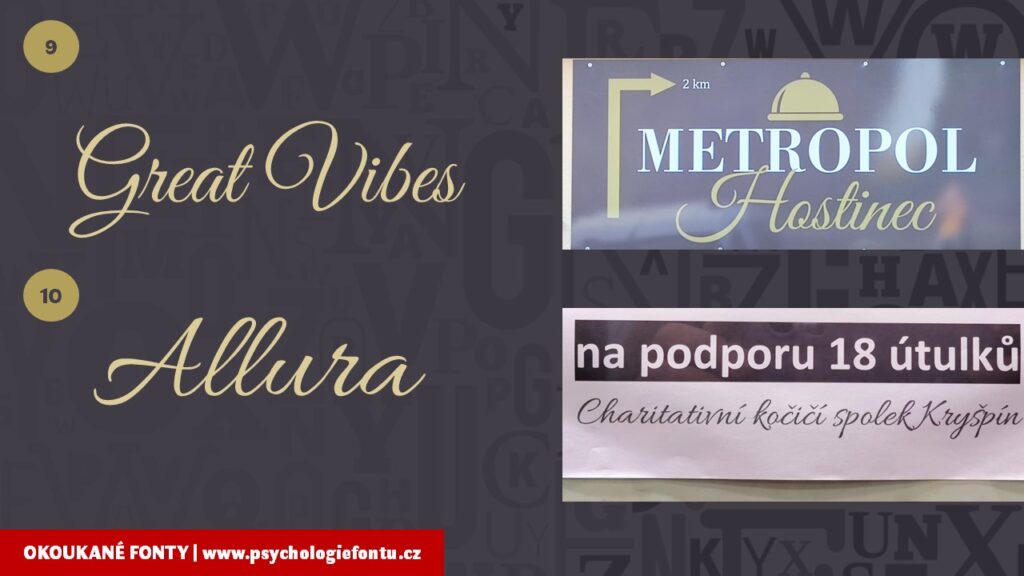
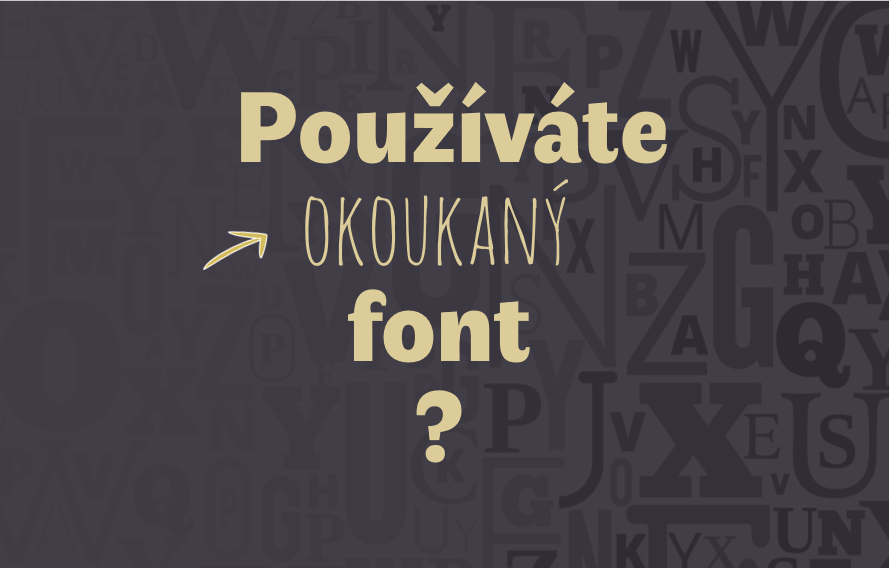
Jsou jako trpaslíci. Skáčou na vás i z ledničky, a to doslova. Fonty, které můžete potkat na ceduli „párek v rohlíku“, na oznámení Českých drah i na vývěsním štítu Beauty salonu. Mluvíme o fontech, které používají miliony lidí na celém světě bezmyšlenkovitě a bez záměru.
Fontech okoukaných.
A takové nechcete. Pokud nemáte rádi trpaslíky.
Pozor, ve většině případů to nejsou fonty špatné, naopak. Až na skupinu fontů amatérských, které náhodou spadnou do aktuálního trendu a stanou se na pár týdnů slavnými. Okoukané fonty mají tu smůlu, že byly zajímavé, originální a snadno dostupné. A v té kombinaci je zakopaný pes.
Sáhnete po nich bezmyšlenkovitě, často jako první volbu, a vůbec netušíte, že se jejich použitím stáváte jedním z mnoha identických trpaslíků. V lepším případě. Protože v horším případě potkáte spoustu lidí, kteří jsou na trpaslíky alergičtí. A na okoukané fonty také.
To, že je font okoukaný, může mít různé důvody. Pojďme si je prozkoumat. A hlavně, pojďme se podívat na to, které fonty to jsou, ať se jim můžete vyhnout.
Ano, okoukaných fontů je mnohem více, toto je výběr. Ano, je to výběr subjektivní, založený na 10leté praxi člověka, který denně analyzuje úplně každý font, který potká, ať online nebo offline.
Neberte si osobně, pokud v ukázkách najdete i váš font, ale vezměte to jako příležitost zase se o kousek posunout dál a vyměnit ho.
Jsou jako Mončičáci (pro pamětníky) nebo Labubu.
Každá doba má své fonty, které frčí. Možná prezentují energii doby, možná potřeby lidí a možná je to náhoda. Možná font použila nějaká celebrita, kterou kopírují tisíce obdivovatelů.
Průkopníkem tohoto trendu byl nešťastný Comic Sans, který doplatil na svou originalitu (ano, Comic Sans BYL ve své době originální!). První font z kategorie handwriting mezi patkovými a bezpatkovými fonty. Navržený Vincentem Connarem r. 1994, speciálně pro komiks o pejskovi Roverovi.
A jak dopadl. Dopracoval to až ke vzniku celosvětového hnutí Ban Comic Sans, strhávání všech tiskovin, na kterých byl použitý z výloh a jejich ostentativní ničení. Stojí za nejedním nervovým tikem grafických designérů, kteří se snaží diplomaticky odmítnout nejoblíbenější font klienta.
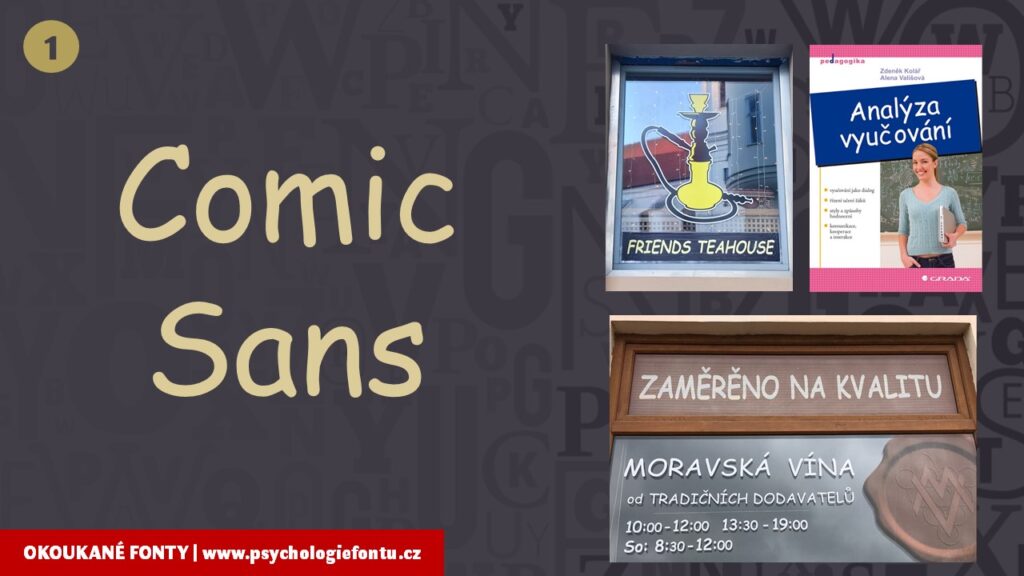
A je mu nahouby, že je neformální, přátelský a velmi dobře čitelný. Že ho milují lidé s dyslexií, děti a lidé slabozrací, protože se jim opravdu dobře čte.
Ale pověst je pověst, abyste si nezadali a nespustili se s „persona ingrata“, nezbývá, než okoukané fonty nahradit jinými, které v sobě nemají negativní podtext „šmarjá už zase!“.
Třeba u hollywoodského trháku, který má rozpočet v miliardách, vám použití druhého nejvíce okoukaného fontu, který je pro grafiky noční můrou, hlava nebere…
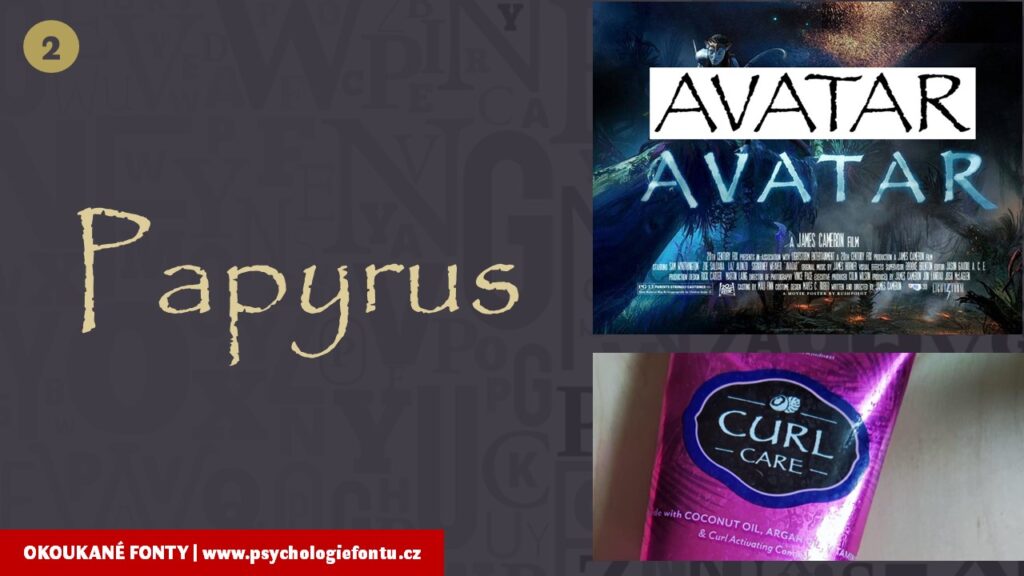
Příklady některých z „populárních“ fontů, které vévodily v popularitě v posledních 10 letech:
Comic Sans, Papyrus, Segoe Script, Amatic SC, Algerian, Scriptina (Ze stejné škatulky jako Scriptina je okoukané Zapfino).
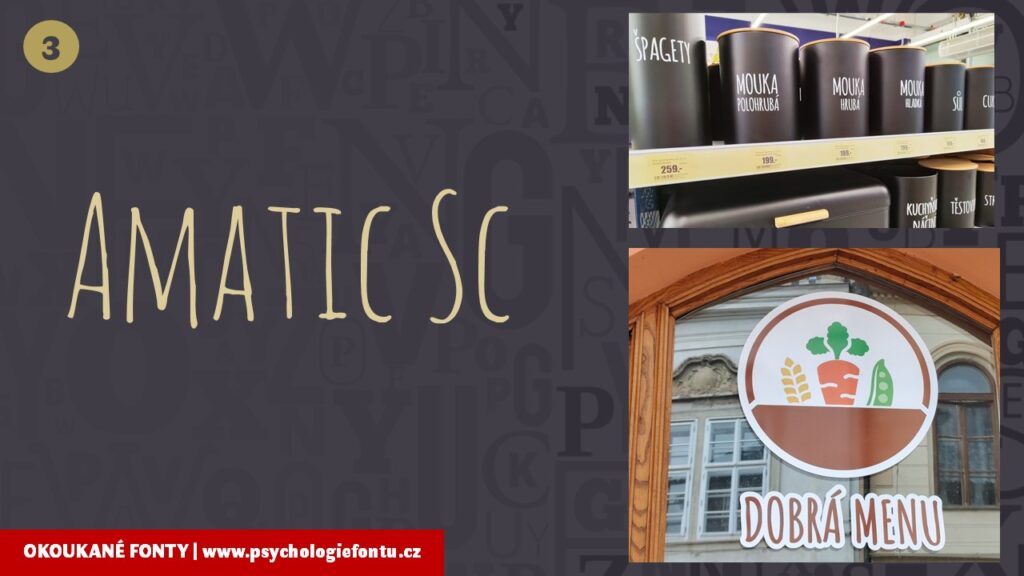
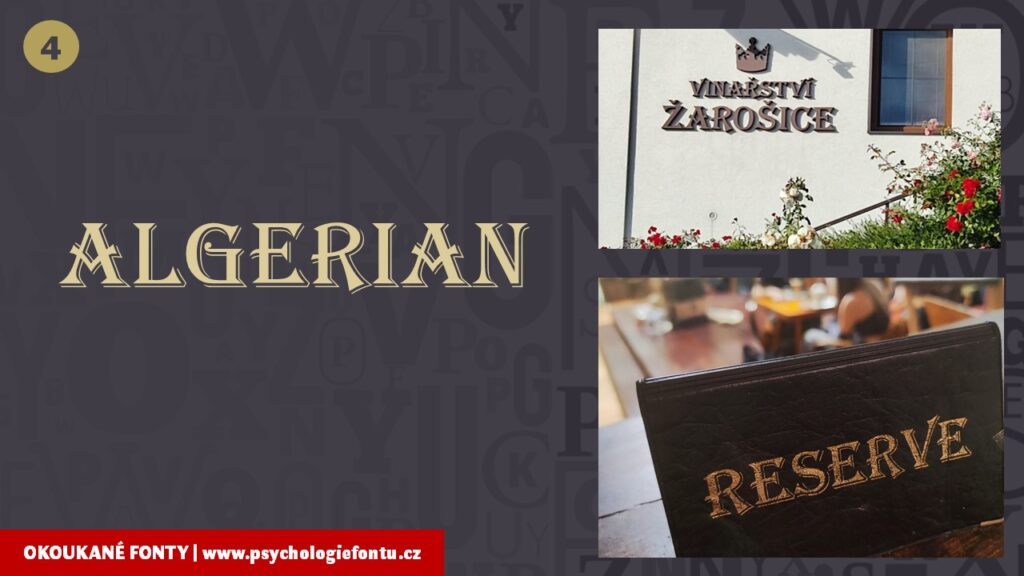
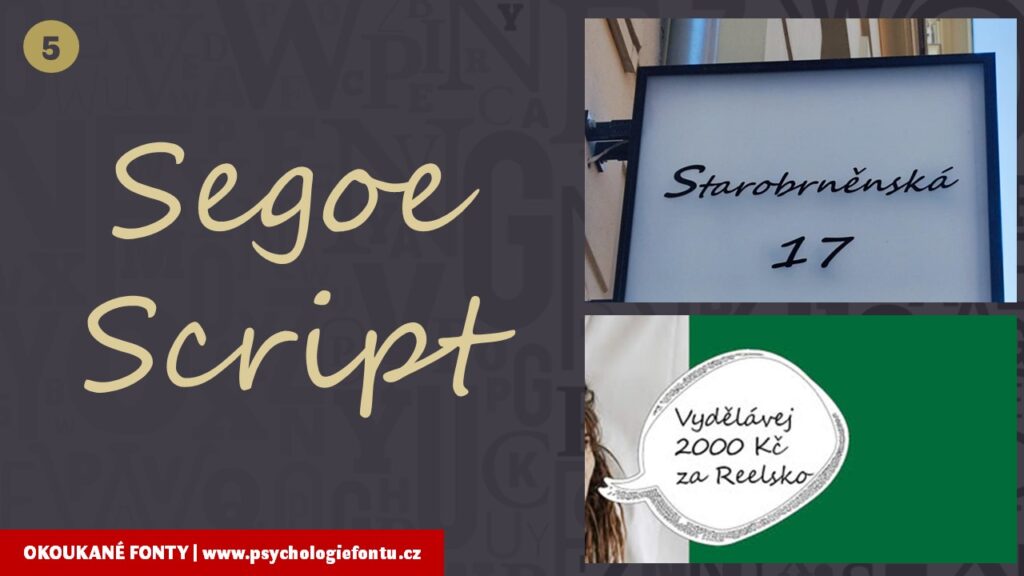
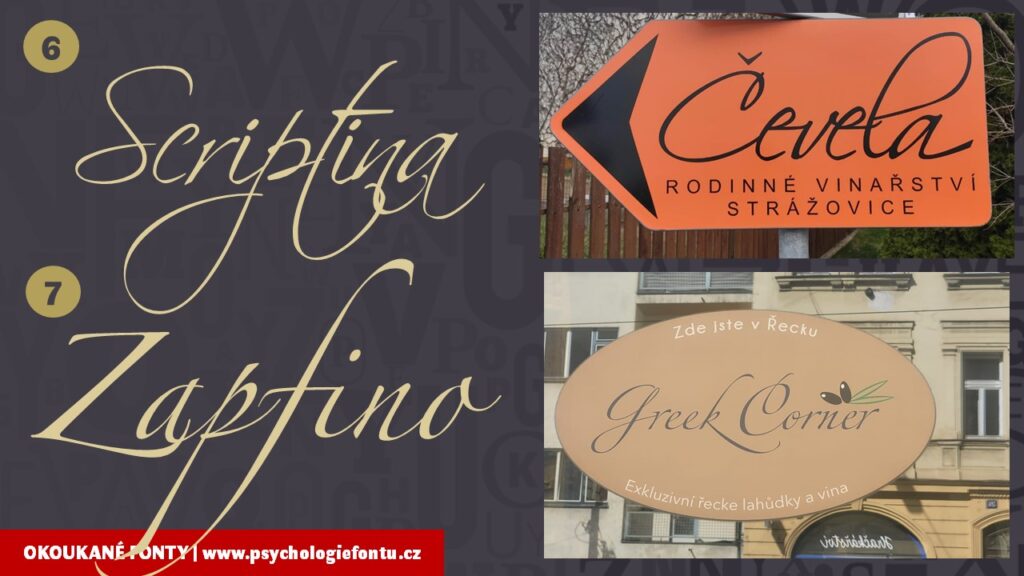
Jé, ten je hezký! Ten se mi líbí, ten chci taky!
Okoukané fonty jsou většinou velmi líbivé. Proč myslíte, že v první desítce jsou Scriptina a Zapfino! Když se zamyslíme, je to logické. Kdo by nechtěl mít na webu font, který se zdá většině lidí zajímavý a hezký! A tak do této kategorie spadají fonty, které jsou trendy a hrají na krásnou nebo romantickou notu.
Co se jim musí nechat, umí zaujmout a umí vzbudit emoce. Zvlášť u žen, muže až na výjimky odradí. Funguje to jako trendy v oblečení:
Klientka Soňa: „Chci ty šaty, které má XY, jsou božské!“
Ale už nevnímá, že paní XY má postavu typu přesýpací hodiny, zatímco Soňa je jako Twiggy, šaty mají rudou barvu, kterou Soňa nikdy nenosí, atd.
A tak pokud ke mně někdo přijde na konzultaci, kde vybíráme font na web, s touhou „mít font, který má XY, protože je boží“, usměju se a vím, že to bude zajímavý proces hledání vlastní identity značky.
Líbivost má totiž bohužel i druhou stránku. Je povrchní, nepředává žádné hlubší a niternější hodnoty a je nevyhnutelné, že časem vyjde z módy.
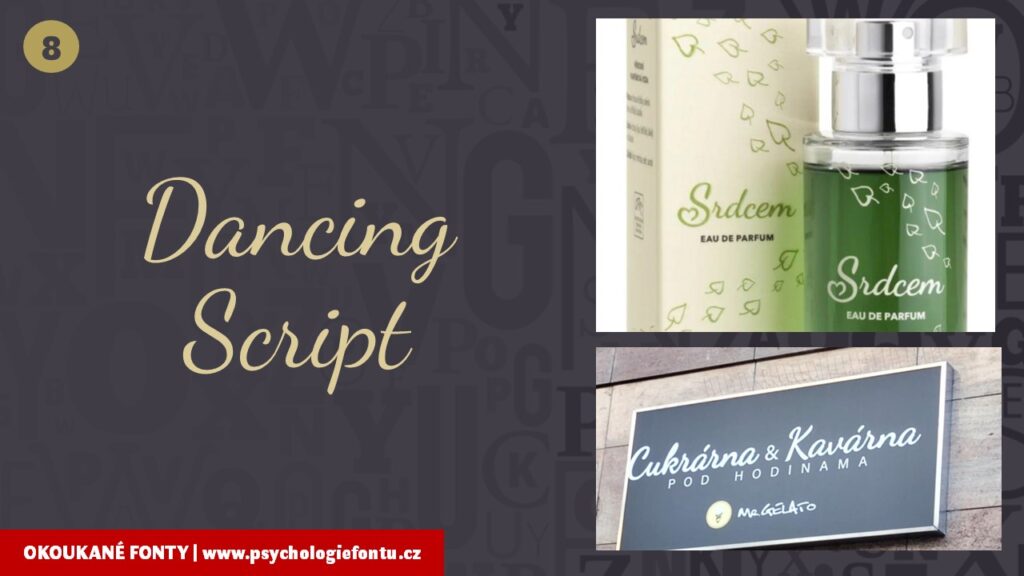
Proto použít takový font na webu nebo ve vizuální identitě je podnikatelská sebevražda.
Nikdo.
Takže pokud nechcete módní doplněk na jednu sezonu, líbivé fonty nebrat.
A hlavně, to, že vám líbivý font přitáhne spoustu lidí, kterým se bude líbit, může přitáhnout i spoustu problémů.
Pokud nebudou vaše cílová skupina, stejně si nic nekoupí a ke článkům a příspěvkům budou mít nerelevantní připomínky.
Pokud nebude ladit s vámi, lidé budou při osobním kontaktu překvapení, zmatení a možná i zklamaní. Font je hravý, zábavný, kreativní, a pak potkají uzavřeného introverta?
Mám v tom 10ti letou praxi a řeknu vám, psychologie fontů je vždy dobrodružství a alchymie.